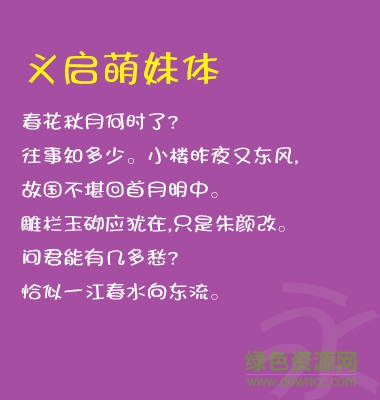
義啟萌妹體字體是一款萌萌噠字體,字體圓潤憨態(tài)可掬,用在廣告設(shè)計(jì)、平面設(shè)計(jì)或ps中效果都非常好,賣萌必備字體,需要的小伙伴快來綠色資源網(wǎng)下載吧!
義啟萌妹體從筆畫的圓轉(zhuǎn)到結(jié)構(gòu)的內(nèi)放外收無不自然天真可愛至極,整體章法更是左右呼應(yīng),表面萌態(tài)無章法實(shí)則章法嚴(yán)謹(jǐn)。